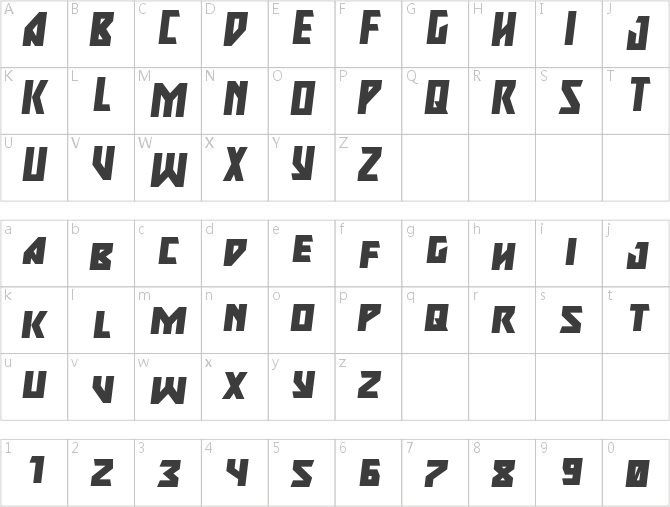
Major Force Expanded Italic 詳情頁
Major Force Expanded Italic字體字庫是一款讓人賞心悅目、百看不厭的英文字體,適合各類廣告和產(chǎn)品包裝設(shè)計應(yīng)用,字體大小0.02MB,格式為ttf字體,上傳用戶是誠澤永信,作者/版權(quán)方為未知